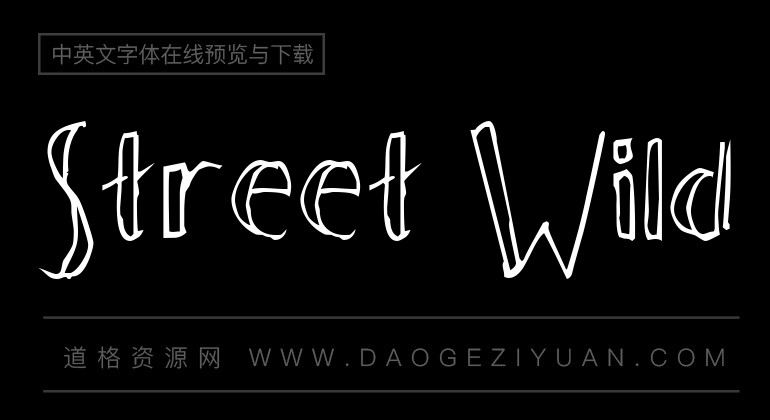
Street Wild
Street Wild是一款极具街头风格的字体,它具有强烈的街头感,带有抢眼的外观效果。它的字体特征包括粗犷、活泼、有力、可爱、时尚的样式,适合用于品牌标识、海报设计等。它的字形独特,充满活力,能够更好地表达出品牌的个性。
Street Wild是一款非常不错的手写艺术字体,具有很好的视觉感,适合于文化类的宣传设计、商业类品牌的广告和产品包装设计以及个性化文字排版等较多场景。